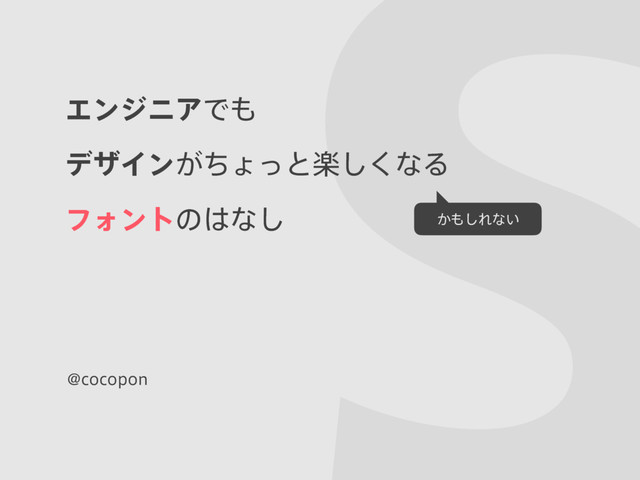
A short story about a developer who love font
エンジニアでもデザインがちょっと楽しくなる(かもしれない)、フォントのはなし。
ひとりのエンジニアが「フォント沼」にハマったお話をします。
1. ༗໊ॻମͷղઆ΍ Gill Sans ABCDEFGHIJKLMNOPQRSTUVWXYZ abcdefghijklmnopqrstuvwxyz Helvetica ABCDEFGHIJKLMNOPQRSTUVWXYZ abcdefghijklmnopqrstuvwxyz Eulostile ABCDEFGHIJKLMNOPQRSTUVWXYZ
abcdefghijklmnopqrstuvwxyz Avenir ABCDEFGHIJKLMNOPQRSTUVWXYZ ࠷΋൚༻తͳαϯηϦϑମͰɺ
ϘʔϧυମͳͲ͸19ੈلάϩ
ςεΫͷߥ࡟Γͳ… େจࣈ͸ಊʑͱͨ͠ݹయతͳ
ࠎ֨Λ͍࣋ͬͯͯɺͲͪΒ͔
ͱ͍͏ͱΠΪϦε෩Ͱ͕͢ɺ… ແػతɺগ͠SFͬΆ͍ۙ୅త
ͳײ͡Ͱ͢ɻ60೥୅͔Β70೥
୅ʹ͔͚ͯྲྀߦͨ͠ॻମͰɺ… ચ࿅ɺۙ୅తɻزԿֶతͳࣈܗ ͳ͕Β΋ɺͲ͔͜ਓؒຯΛײ͡
2. ࣌୅͝ͱͷॻମͷભҠ΍ ੈل͔Βੈل w 0NOJB w )BNNFS/V[JBMF ੈل͔Βੈل w %VD%F#FSSZ w
/PUSF%BNF w "MUF4DIXBCBDIFS w 8JMIFMN,MJOHTQPS(PUJTDI ੈل w 5IPSPXHPPE w &HZQUJBO w 1MBZCJMM w .BEBNF w )BXUIPSO w $BSMUPO w #FSOIBSE w 'SBOLMJO(PUIJD
3. Ͳͷ͘Β͍ͷߦ͕ؒಡΈ΍͍͢ΜͩΖ͏ʁ Lorem ipsum dolor sit amet, consectetur adipiscing elit. Maecenas
ultricies ante ipsum, ac pharetra arcu auctor facilisis. Donec auctor quam augue, non pharetra nunc sodales nec. Nullam consectetur, ante sed tincidunt euismod, nulla felis hendrerit nibh, ut aliquet turpis lacus et tellus. Proin bibendum feugiat velit, eu cursus arcu aliquam a. Pellentesque ultricies massa nec velit aliquam feugiat. Aliquam feugiat lacus vitae nulla interdum fermentum. In pulvinar bibendum ante quis posuere. Suspendisse ut lacus in nunc sagittis convallis eget sit amet sapien. Sed convallis vitae dolor sed rutrum. In quis justo a lacus scelerisque mollis sit amet a augue. Lorem ipsum dolor sit amet, consectetur adipiscing elit. Aenean sodales ac lorem ac hendrerit. Nulla quis accumsan orci, sit amet sollicitudin mauris. Praesent ipsum eros, pellentesque vitae sodales ut, blandit ut erat. Maecenas ut dapibus erat. Nullam in sapien eleifend, mollis urna venenatis, vestibulum libero. Suspendisse eget accumsan sem, ac viverra arcu. Fusce hendrerit augue id tempor tristique. Nullam nec neque tincidunt, elementum nibh eget, suscipit urna. Praesent nec sapien facilisis, condimentum lorem vel, semper felis. Pellentesque sed dui a lorem dictum rhoncus et at elit. Integer scelerisque finibus aliquet. Nulla lacinia, turpis ac fringilla rutrum, elit purus varius urna, a tristique risus mauris a dui. Proin mauris arcu, finibus eget ipsum eget, auctor ultricies elit. Lorem ipsum dolor sit amet, consectetur adipiscing elit. Maecenas ultricies ante ipsum, ac pharetra arcu auctor facilisis. Donec auctor quam augue, non pharetra nunc sodales nec. Nullam consectetur, ante sed tincidunt euismod, nulla felis hendrerit nibh, ut aliquet turpis lacus et tellus. Proin bibendum feugiat velit, eu cursus arcu aliquam a. Pellentesque ultricies massa nec velit aliquam feugiat. Aliquam feugiat lacus vitae nulla interdum fermentum. In pulvinar bibendum ante quis posuere. Suspendisse ut lacus in nunc sagittis convallis eget sit amet sapien. Sed convallis vitae dolor sed rutrum. In quis justo a lacus scelerisque mollis sit amet a augue. Lorem ipsum dolor sit amet, consectetur adipiscing elit. Aenean sodales ac lorem ac hendrerit. Nulla quis accumsan orci, sit amet sollicitudin mauris. Praesent ipsum eros, pellentesque vitae sodales ut, blandit ut erat. Maecenas ut dapibus erat. Nullam in sapien eleifend, mollis urna venenatis, vestibulum libero. Suspendisse eget accumsan sem, ac viverra arcu. Fusce hendrerit augue id tempor tristique. Nullam nec neque tincidunt, elementum nibh eget, suscipit urna. Praesent nec sapien facilisis, condimentum lorem vel, semper felis. Pellentesque sed dui a lorem dictum rhoncus et at elit. Integer scelerisque finibus aliquet. Nulla lacinia, turpis ac fringilla rutrum, elit purus varius urna, a tristique risus mauris a dui. Proin mauris Lorem ipsum dolor sit amet, consectetur adipiscing elit. Maecenas ultricies ante ipsum, ac pharetra arcu auctor facilisis. Donec auctor quam augue, non pharetra nunc sodales nec. Nullam consectetur, ante sed tincidunt euismod, nulla felis hendrerit nibh, ut aliquet turpis lacus et tellus. Proin bibendum feugiat velit, eu cursus arcu aliquam a. Pellentesque ultricies massa nec velit aliquam feugiat. Aliquam feugiat lacus vitae nulla interdum fermentum. In pulvinar bibendum ante quis posuere. Suspendisse ut lacus in nunc sagittis convallis eget sit amet sapien. Sed convallis vitae dolor sed rutrum. In quis justo a lacus scelerisque mollis sit amet a augue. Lorem ipsum dolor sit amet, consectetur adipiscing elit. Aenean sodales ac lorem ac hendrerit. Nulla quis accumsan orci, sit amet sollicitudin mauris. Praesent ipsum eros, pellentesque vitae sodales ut, blandit ut erat. Maecenas ut dapibus erat. Nullam in sapien eleifend, mollis urna venenatis, vestibulum libero. Suspendisse eget accumsan sem, ac viverra arcu. Fusce hendrerit augue id tempor tristique. Nullam nec neque tincidunt, elementum nibh eget, suscipit urna. Praesent nec sapien αΠζQU ߦૹΓQU ͜ͷ͋ͨΓͷ͓΋͠Ζ͕͞Θ͔ͬͯ͘Δͱɺઌͷখ࿩ͷ݅͸ղܾͦ͠͏Ͱ͢Ͷ
4. ݟग़͠ͱຊจͷϑΥϯτɺͲ͏૊Έ߹ΘͤΔʁ Lorem ipsum dolor sit amet, consectetur adipiscing elit. Maecenas
ultricies ante ipsum, ac pharetra arcu auctor facilisis. Donec auctor quam augue, non pharetra nunc sodales nec. Nullam consectetur, ante sed tincidunt euismod, nulla felis hendrerit nibh, ut aliquet turpis lacus et tellus. Proin bibendum feugiat velit, eu cursus arcu aliquam a. Pellentesque ultricies massa nec velit aliquam feugiat. Aliquam feugiat lacus vitae nulla interdum fermentum. In pulvinar bibendum ante quis posuere. Suspendisse ut lacus in nunc sagittis convallis eget sit amet sapien. Sed convallis vitae dolor sed rutrum. In quis justo a lacus scelerisque mollis sit amet a augue. Lorem ipsum dolor sit amet, consectetur adipiscing elit. Aenean sodales ac lorem ac hendrerit. Nulla quis accumsan orci, sit amet sollicitudin mauris. Praesent ipsum eros, pellentesque vitae sodales ut, blandit ut erat. Maecenas ut dapibus erat. The quick brown fox jumps over Lorem ipsum dolor sit amet, consectetur adipiscing elit. Maecenas ultricies ante ipsum, ac pharetra arcu auctor facilisis. Donec auctor quam augue, non pharetra nunc sodales nec. Nullam consectetur, ante sed tincidunt euismod, nulla felis hendrerit nibh, ut aliquet turpis lacus et tellus. Proin bibendum feugiat velit, eu cursus arcu aliquam a. Pellentesque ultricies massa nec velit aliquam feugiat. Aliquam feugiat lacus vitae nulla interdum fermentum. In pulvinar bibendum ante quis posuere. Suspendisse ut lacus in nunc sagittis convallis eget sit amet sapien. Sed convallis vitae dolor sed rutrum. In quis justo a lacus scelerisque mollis sit amet a augue. Lorem ipsum dolor sit amet, consectetur adipiscing elit. Aenean sodales ac lorem ac hendrerit. Nulla quis accumsan orci, sit amet sollicitudin mauris. Praesent ipsum eros, pellentesque vitae sodales ut, blandit ut erat. Maecenas ut dapibus erat. The quick brown fox jumps over